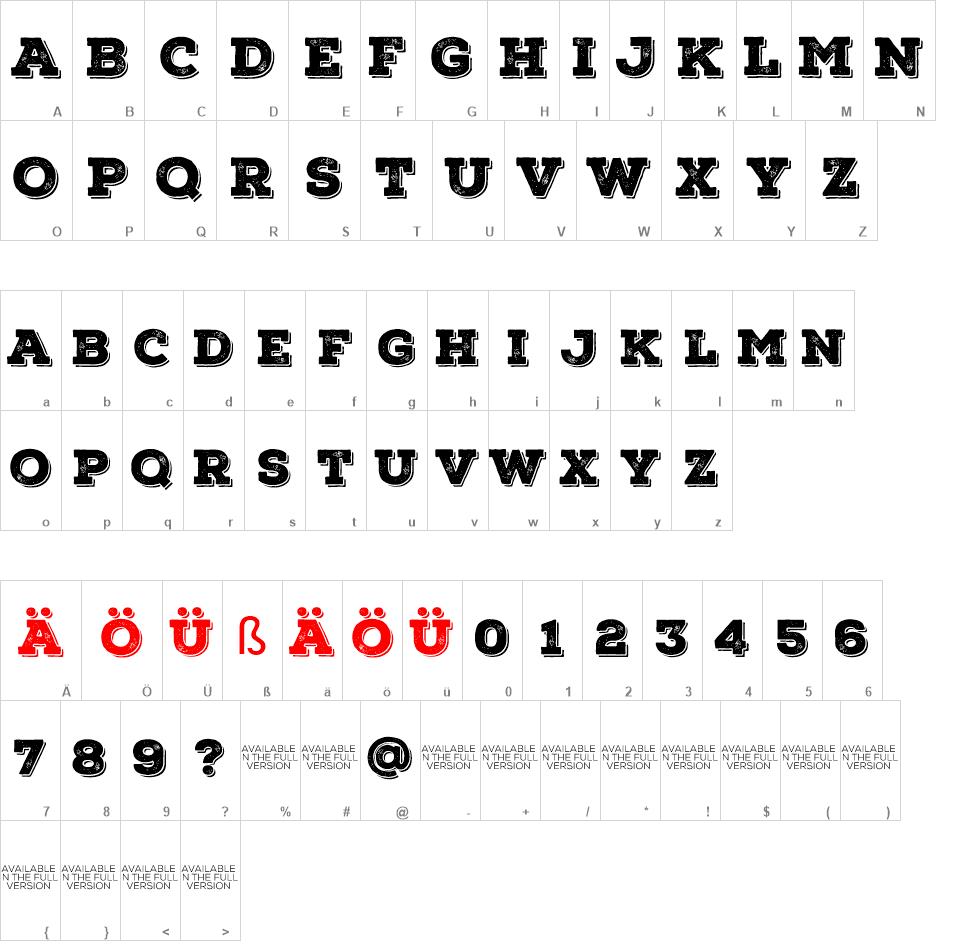
Nexa Rust
Nexa Rust von Fontfabric Type Foundry ist ein vielseitiges Zeichensystem, das aus den Unterfamilien Sans, Flooring, Command, Handmade und Extras besteht. Jede dieser Unterfamilien hat ein charakteristisches warmes, raues Aussehen und einige Sättigungsgrade.